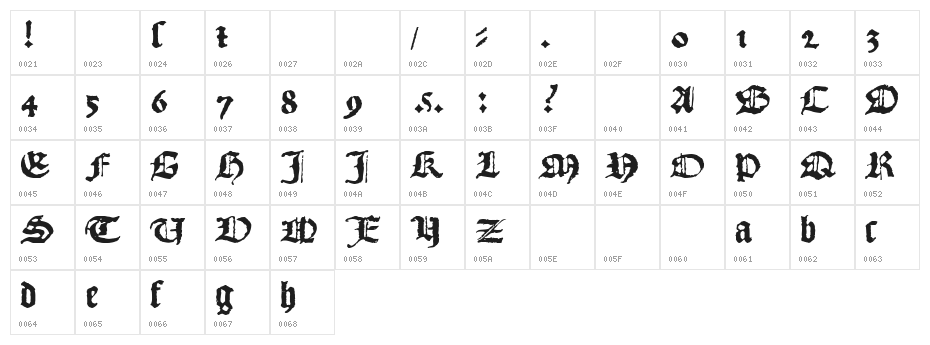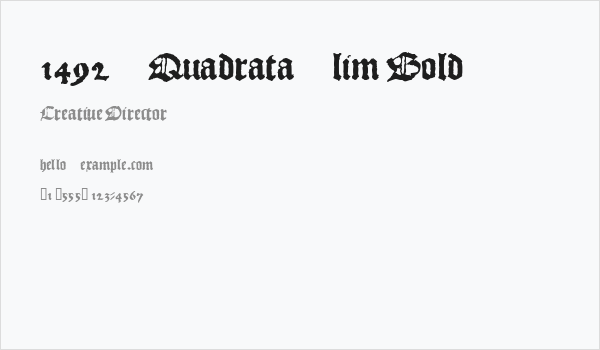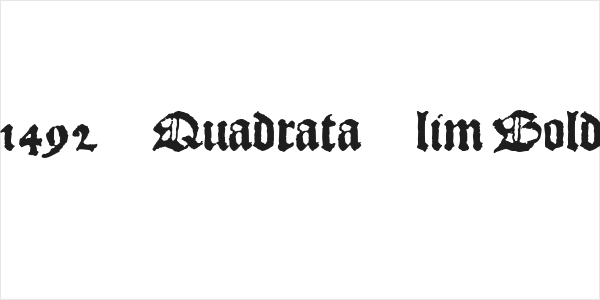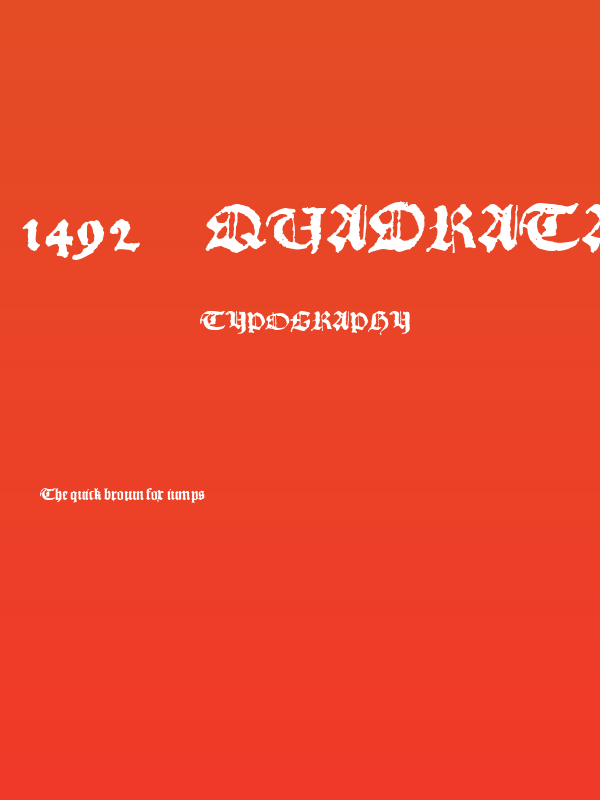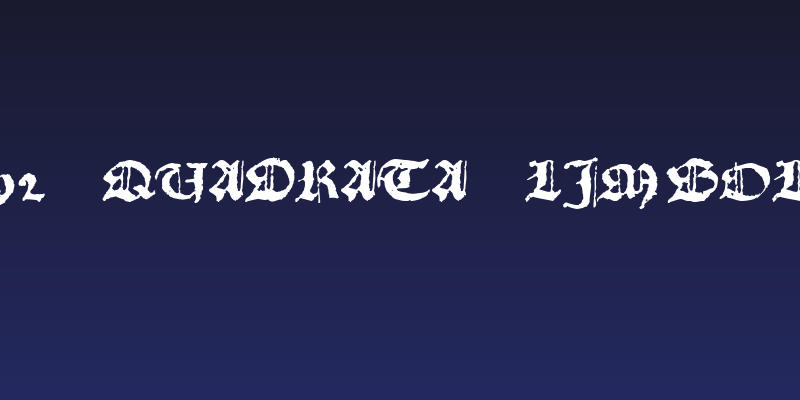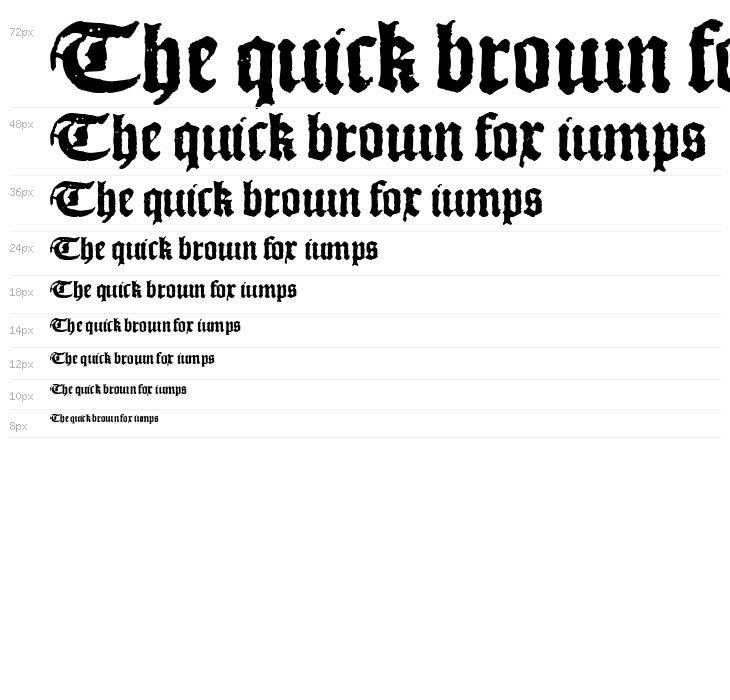
1492_Quadrata_lim Bold Font
| Gesamtstil | Classic |
| Anwendungsfall | Headlines, Logos, Decorative text |
| Vorgeschlagene Projekte | Ideal for historical documents, certificates, wedding invitations, and branding that requires a traditional or gothic touch. |